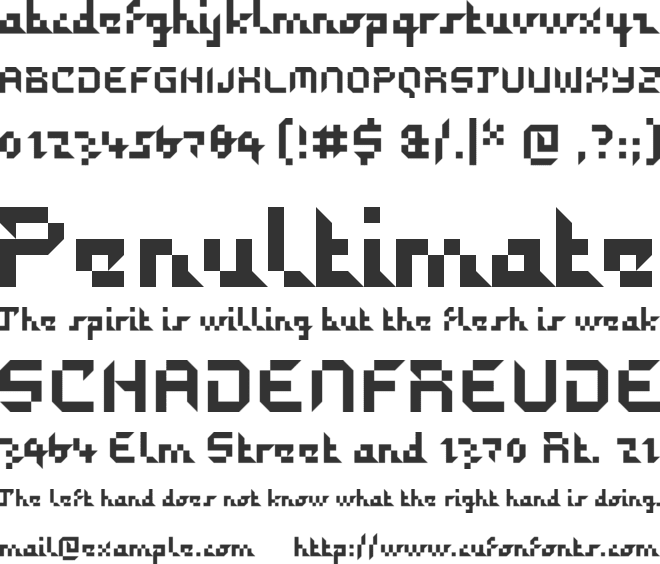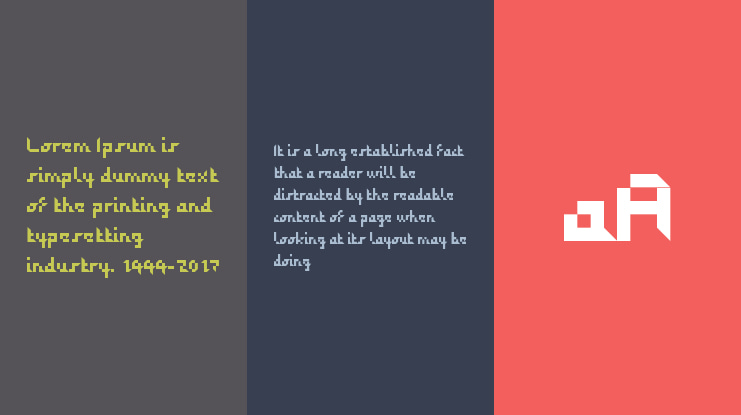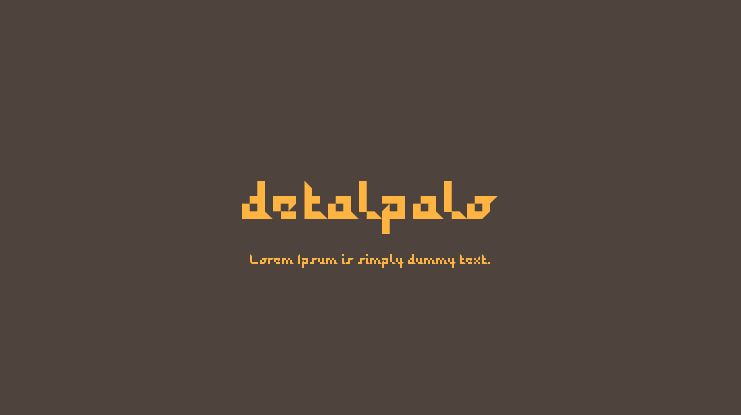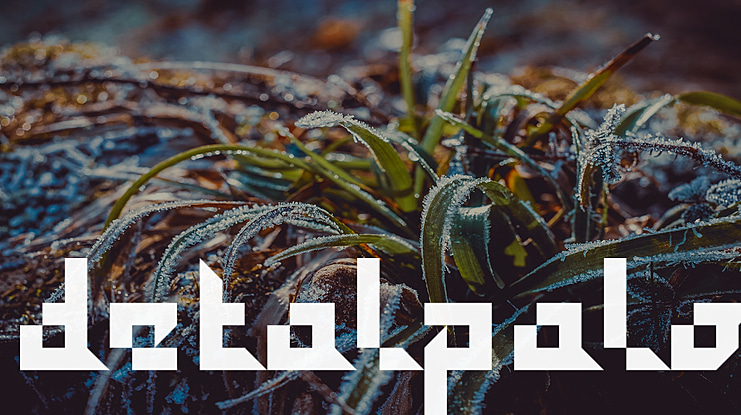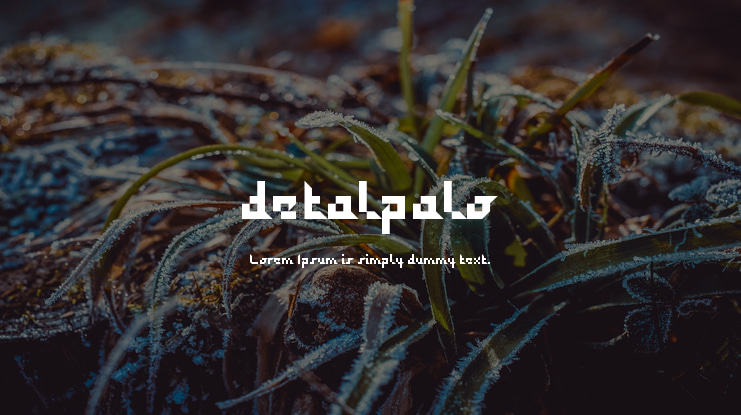
detalpalo Font
Diseño experimental de familia tipográfica desarrollada para una colección/exposición/muestra realizada en Nolup (argentina) por el grupo IXS. Libre para cualquier tipo de uso, salvo proyectos estrictamente comerciales. www.facebook.com/ideasxs www.facebook.com/nolup.laboratorio www.behance.net/piterosporum